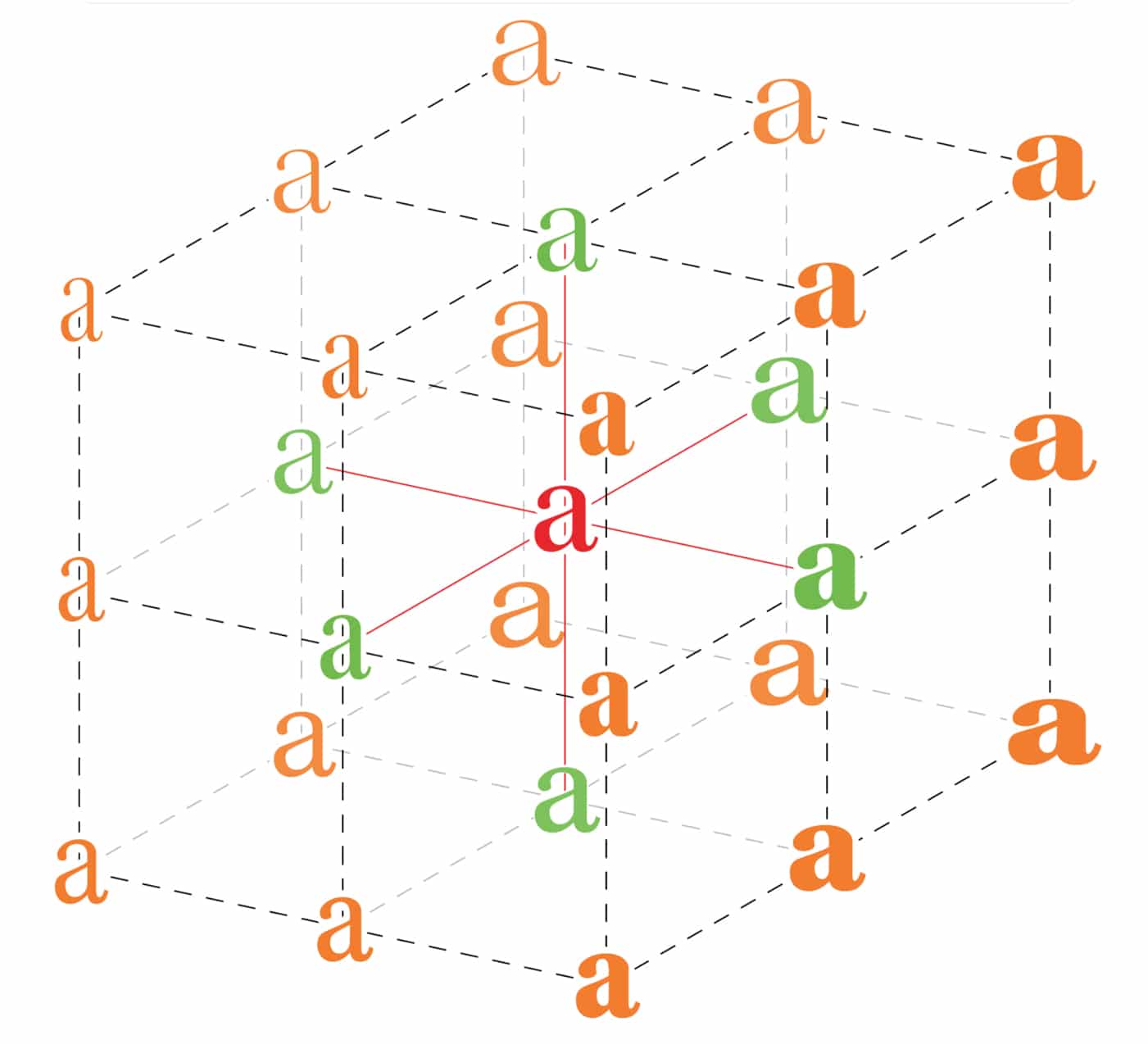
Variable Fonts – die neue Freiheit im Schriftenkosmos?
Nach Opentype- und Webfonts schicken sich Variable Fonts gerade an, die Typografie zu revolutionieren. 2016 eingeführt, haben mittlerweile nahezu alle Schriftenhersteller variable Fonts im Programm. Ein kleines Schriftenuniversum in einem einzigen Font, die Stile stufenlos per Schieberegler generierbar – was genau steckt dahinter?
Schön neue Typografie-Welt?
Zu Bleisatzzeiten gab es in den Druckereien eine überschaubare Anzahl Satzschriften, mit einem begrenzten Angebot an unterschiedlichen Strichstärken und Laufweiten. Dies änderte sich in der Frühzeit der Fotosatzes; 1957 ersann Adrian Frutiger für seine Univers-Familie eine 21 Schriftschnitte umfassende Systematik. In den 1980ern entstanden die ersten, aus verschiedenen Stilen bestehenden Schriftsippen – geradezu legendär ist die von Kurt Weidemann zwischen 1985 und 1989 für Daimler-Benz entworfene Corporate A-S-E, mit fast fünfzig Schriftschnitten.
In den Folgejahren wurden die Schriftfamilien immer größer, die Musterbücher immer dicker. Ein hoher technischer Aufwand, im Dienste von Differenzierung (zum Beispiel in der Buchtypografie) und Vielfalt (beispielsweise in Werbung und Markendesign).
Interpolation
Variable Fonts funktionieren nach demselben Grundprinzip: Zwischen festgelegten fixen Vorlagen lassen sich per Schieberegler alle Zwischenstufen automatisch generieren; die Zahl der Achsen kann je nach Schriftstil variieren, hier ein Beispiel für fünf Achsen:
- Strichstärke
- Weite
- Optische Größe
- Kursive (italic)
- Schräge (slanted)
Achsen können außerdem für Serifen angelegt sein oder für eine dekorative Ausgestaltung der Grundstriche (Skelett); ein schönes Beispiel dafür ist die Decovar von David Berlow (Font Bureau). Auf fontbureau.typenetwork.com findet man die Schrift und kann nach Herzenslust aus einer Serifenlosen eine verschnörkelte oder eine gestreifte Version zaubern, außerdem stehen zehn unterschiedliche Serifenformen zur Auswahl.
Die mathematisch interpolierten Schnitte der Multiple-Master-Fonts konnten nicht die gleiche ästhetische Qualität haben wie eine Satzschrift mit einzelnen, optisch optimierten Schnitten. Je kleiner der Schriftgrad, umso offener und einfacher müssen die Buchstabenformen sein, bei zugleich geringfügig vergrößerter Laufweite und etwas stärkerer Strichstärke. Die Stempelschneider der Bleisatzzeit wussten das, die Schriftenhersteller der frühen Fotosatzjahre vergaßen es zeitweilig, inzwischen gibt es längst wieder Fonts, die über optische Größen verfügen.
Die Voraussetzungen für einen Erfolg variabler Fonts sind günstig. Erstens weil Adobe, Apple, Google und Microsoft das neue Fontformat gemeinsam entwickelt und es in die Opentype-Spezifikation übernommen haben; zweitens weil mit der Webtypografie ein ganz neuer Anwendungsbereich hinzugekommen ist. Variable Fonts sind dafür prädestiniert. Und sie haben einen Vorteil gegenüber Webfonts: Ihr Datenvolumen ist kleiner. Gut für einen schnellen Ladevorgang. [13583]